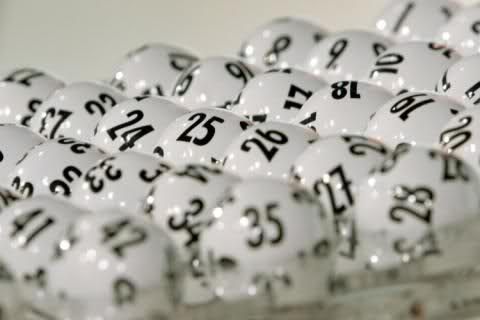
Schriftart auf den Lottokugeln
ich suche die Schriftart der offiziellen Lottokugeln wie auf dem Foto zu sehen.
irgendeine futura condensed, würde ich sagen.
… mit nachträglich dazugemaltem Querbalken für die Sieben. War wahrscheinlich gewünscht, um Verwechslungen mit der Eins auszuschließen, sieht aber trotzdem etwas schräg aus.
Ivo hat hier mal eine Liste von Schriften mit 7-Strich gemacht.